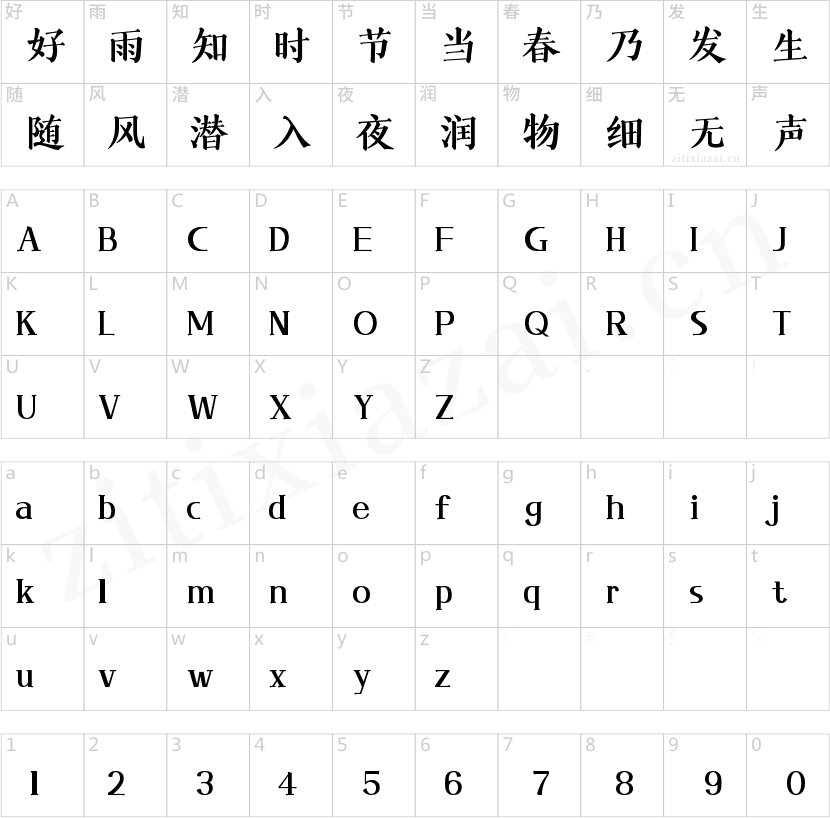
字魂太阿楷书
字魂太阿楷书,这款字体结构工整、笔画清晰,兼顾美观与易读性,适用于标题、正文、海报、包装、LOGO 等多种场景。字形优雅稳定,风格百搭耐看,适配日常排版与创意设计,让文字呈现更舒适、更具质感。字魂太阿楷书一笔一画,皆是细节,以均衡的比例、流畅的线条打造舒适视觉体验,字形端正大气,风格简约现代。无论是商业设计、品牌宣传还是日常排版,都能轻松驾驭,让文字更有格调与力量。字魂太阿楷书字体下载。